En esta publicación de blog, compartiremos contigo las 18 mejores fuentes de bordado que seguramente mejorarán el atractivo visual de tus diseños.
Pero quizás te preguntes, ¿cómo elijo la fuente correcta? ¿Estas fuentes funcionarán bien con mis proyectos? ¡No te preocupes, lo tenemos cubierto!
En este artículo, profundizaremos en el mundo de las fuentes de bordado y mostraremos las 18 opciones principales que han sido cuidadosamente seleccionadas por su singularidad, versatilidad y atractivo estético.
Pero antes de profundizar, tomemos un momento para considerar la importancia de elegir la fuente adecuada para sus proyectos de diseño.
¿Sabías que la fuente que elijas puede tener un gran impacto en la apariencia general de tu diseño? Puede transmitir emociones, marcar el tono e incluso influir en cómo la audiencia percibe su trabajo.
No se trata sólo de seleccionar cualquier fuente, sino de encontrar la combinación perfecta que complemente su proyecto y cree una experiencia visual armoniosa. Entonces, ¡exploremos las 18 mejores fuentes de bordado que te ayudarán a llevar tus diseños al siguiente nivel!
Ahora que hemos tocado la importancia de seleccionar la fuente correcta, comencemos nuestra exploración de las 18 mejores fuentes de bordado. En este artículo, mostraremos una amplia gama de fuentes, cada una con su estilo y encanto únicos.
Desde elegantes fuentes script hasta opciones atrevidas y divertidas, hay algo para cada proyecto y preferencia personal. Ya sea que estés trabajando en un logotipo, materiales de marca o una ilustración digital, estas fuentes agregarán un toque de sofisticación y creatividad a tus diseños.
Entonces, ¿estás listo para descubrir las 18 mejores fuentes de bordado? Prepárate para dar rienda suelta a tu creatividad y llevar tus diseños a nuevas alturas con estas opciones cuidadosamente seleccionadas.
Estén atentos mientras lo guiamos a través de cada fuente, resaltamos sus características clave y brindamos ejemplos de la vida real de cómo se pueden usar. ¡Prepárate para impresionar a tus clientes y cautivar a tu audiencia con la fuente de bordado perfecta!
Las mejores fuentes de bordado premium
Bienvenido al mundo de las fuentes de bordado premium, donde cada puntada cuenta una historia. Prepárate para mejorar tus proyectos de diseño con estas fuentes de primer nivel que garantizan que tus creaciones destaquen.
Entonces, toma tus agujas e hilo y únete a nosotros mientras exploramos las mejores fuentes de bordado premium que llevarán tu obra de arte al siguiente nivel. No pierdas la oportunidad de descubrir estas increíbles fuentes: ¡sumérgete y deja volar tu imaginación!
Puntadas
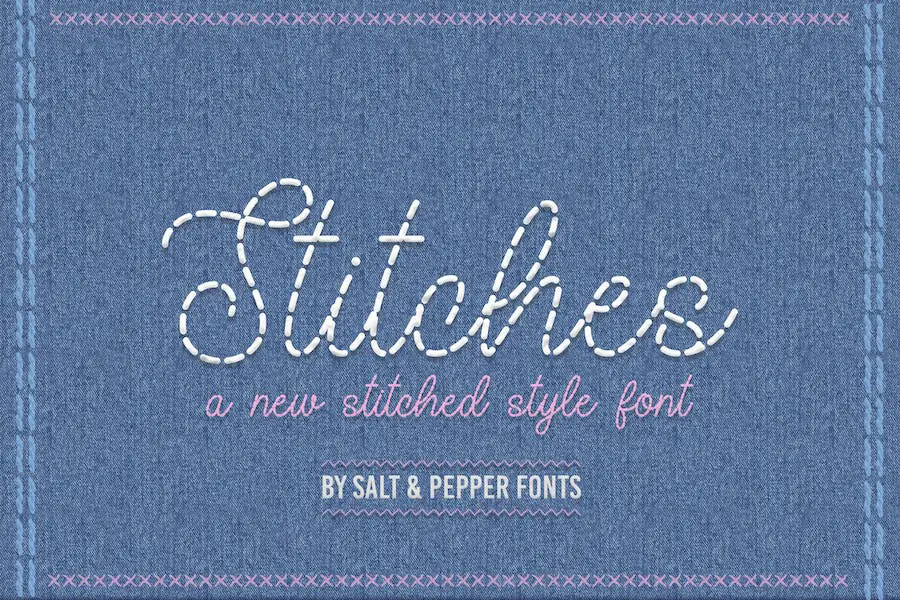
Bienvenido a mi reseña de la fuente Stitches, una fuente de escritorio que aporta el estilo del bordado y la costura a tus proyectos de diseño.
cherolina
Cherolina es una fuente versátil que ofrece un conjunto completo de letras mayúsculas y minúsculas, números, símbolos multilingües, puntuación y ligaduras.
También presenta elementos de diseño únicos, como caracteres decorativos iniciales y finales en minúsculas cortas, así como caracteres decorativos finales en minúsculas, lo que lo convierte en una excelente opción para invitaciones y monogramas.
La textura suave de la fuente la hace adecuada para una variedad de técnicas de impresión, incluido el bordado, el corte por láser y el estampado de oro.
Denalova
Denalova es una fuente de bordado exquisita que ofrece un conjunto completo de letras mayúsculas y minúsculas, junto con símbolos, números, puntuación y ligaduras multilingües.
Lo que distingue a Denalova de otras fuentes es la inclusión de características únicas, como caracteres decorativos iniciales y finales en minúsculas cortas, así como caracteres decorativos iniciales y finales en minúsculas largas.
Con Denalova, los diseñadores gráficos que buscan elevar el diseño de sus proyectos encontrarán una fuente versátil que aporta elegancia y encanto a cualquier diseño. Ya sea que esté trabajando en portadas de libros con un tema medieval o necesite un monograma o una fuente de caligrafía para bordar a máquina o a mano, Denalova seguramente satisfará sus necesidades.
Hermosamente
Beautifully es una fuente script exquisita que combina elegancia, modernidad y un toque de clase. Esta fuente es perfecta para una amplia gama de proyectos de diseño, incluidos logotipos, marcas, invitaciones, papelería, diseños de bodas y publicaciones en redes sociales.
Con sus hermosas curvas y detalles refinados, Beautifully añade un toque de sofisticación a cualquier proyecto. Si eres un diseñador gráfico profesional o alguien que busca mejorar sus proyectos personales, esta fuente seguramente te impresionará.
Es lo suficientemente versátil como para usarse en diferentes plataformas y software, incluidos Google, Adobe, Canva, Circuit, Figma e incluso para diseños de tatuajes. Con Beautifully, puedes lograr sin esfuerzo un resultado pulido y visualmente atractivo. Entonces, ¿por qué esperar? Eleva tus diseños con el fascinante encanto de Beautifully.
Gran belleza gorda
Big Fat Beauty es una fuente Casual Script diseñada para varios proyectos de diseño. Sus atributos lo hacen perfecto para crear un tema informal, logotipos, materiales de marca, carteles, citas, bellos artículos de papelería, publicaciones llamativas en redes sociales y lindas tarjetas de felicitación, entre otros diseños.
Esta fuente es versátil y añade un toque de belleza a cualquier proyecto. Ya sea que sea un diseñador gráfico que trabaja en un logotipo o un blogger que crea publicaciones en las redes sociales, Big Fat Beauty seguramente mejorará su diseño y lo hará destacar del resto.
Entonces, ¿por qué no intentarlo y ver la diferencia que puede marcar en sus proyectos?
Bulvarante
Bulvaryante es una fuente de escritura informal llamada 'Big Fat Beauty'. Es perfecto para una variedad de proyectos de diseño, incluidos temas informales, logotipos, marcas, carteles, citas y hermosos diseños de papelería.
Con su estilo llamativo, también es ideal para crear publicaciones cautivadoras en las redes sociales y lindas tarjetas de felicitación. Esta fuente añade un toque de encanto y singularidad a cualquier diseño.
Café Temprano
Early Coffee es una fuente monolínea manuscrita que sirve para múltiples propósitos. Ya sea que esté buscando agregar un toque de elegancia a su bordado de caligrafía, crear un atractivo letrero de cafetería o menú de cafetería, o simplemente desee una fuente de caligrafía única y moderna, esta fuente lo tiene cubierto.
Su versatilidad se extiende más allá de estas aplicaciones, ya que también se puede utilizar para citas, pancartas, logotipos, empaques de productos, títulos, encabezados, listas de menús y tarjetas de invitación. Esta fuente es perfecta para diversas ocasiones, como baby showers, bodas, cumpleaños, acción de gracias, Navidad y San Valentín.
Con Early Coffee, puedes realzar el diseño de tu proyecto y hacer que se destaque con una fuente manuscrita hermosa y elegante.
rossi
Rossie es una fuente de caligrafía moderna diseñada para agregar un toque elegante, chic y moderno a tus diseños.
Con sus funciones OpenType, que incluyen ligaduras, alternativas, caracteres decorativos finales, números y puntuación, además de compatibilidad con otros idiomas, esta fuente ofrece versatilidad y creatividad.
La textura suave de Rossie lo hace adecuado para diversas técnicas de impresión, como bordado, corte por láser, Cricut y lámina dorada. Ya sea que esté trabajando en un proyecto que requiere sofisticación o buscando una apariencia elegante y contemporánea, Rossie es la elección perfecta.
Historias de llamadas
Callstories es una fuente excepcional que ofrece una variedad de características para mejorar sus proyectos de diseño. Con compatibilidad OpenType, incluye ligaduras, alternativas, caracteres floridos iniciales y finales, números y puntuación.
Esta fuente también es versátil, admite varios idiomas y se adapta bien a diferentes técnicas de impresión como bordado, corte por láser, Cricut y lámina dorada. Su textura suave añade un toque de elegancia, chic y modernidad a tus diseños.
Si buscas una fuente que combine estilo y funcionalidad, Callstories es la elección perfecta para ti.
signatario
Signatie es una fuente de firma elegante que agrega elegancia, elegancia y modernidad a sus diseños. Es perfecto para diseñadores gráficos que desean realzar sus proyectos con un toque de sofisticación.
Esta fuente viene con funciones OpenType, que incluyen ligaduras y caracteres decorativos finales, así como soporte para números, puntuación y múltiples idiomas.
Su textura suave lo hace adecuado para diversas técnicas de impresión como bordado, corte por láser, Cricut y lámina dorada. Con Signatie, puedes crear sin esfuerzo diseños impresionantes y de apariencia profesional.
Arrancador de banda de rodadura
Tread Starter es una fuente de escritura monolínea informal que es perfecta para varios proyectos de diseño.
Sus atributos incluyen ser adecuado para temas informales, logotipos, marcas, carteles, citas, exhibidores, bellos artículos de arte, publicaciones llamativas en redes sociales y lindas tarjetas de felicitación, así como cualquier otro diseño que puedas imaginar.
bosque
Forestea es una fuente de caligrafía moderna que aporta elegancia, elegancia y modernidad a tus diseños.
Con sus características OpenType, que incluyen ligaduras, alternativas, caracteres floridos iniciales y finales, números y puntuación, esta fuente no solo es versátil sino que también admite múltiples idiomas.
Su textura suave lo hace adecuado para diversas técnicas de impresión como bordado, corte por láser, Cricut y lámina dorada. Ya sea que esté trabajando en invitaciones, tarjetas de felicitación, logotipos o cualquier otro proyecto de diseño, Forestea es la elección perfecta.
Las mejores fuentes de bordado gratuitas
¿Busca mejorar sus proyectos de bordado con fuentes únicas y llamativas? ¡No busque más! En este artículo, hemos compilado una lista de las mejores fuentes de bordado gratuitas que seguramente llevarán tus diseños al siguiente nivel.
Así que no te lo pierdas: ¡sigue leyendo y descubre la fuente perfecta para tu próxima obra maestra de costura!
Bordado VTKS
VTKS Bordado es una fuente perfecta para diseñadores gráficos que buscan elevar el diseño de sus proyectos. Es una fuente gratuita creada por Douglas Vitkauskas y está disponible para uso personal.
La fuente VTKS Bordado agrega un toque único a cualquier diseño con sus patrones intrincados y detallados. Presenta un aspecto artesanal, lo que le da a sus proyectos una sensación artística y personalizada.
Esta fuente es una excelente opción para agregar un toque de elegancia y sofisticación a tus diseños.
Puntada Hovden
Hovden Stitch es una fuente de bordado exquisita que es perfecta para diseñadores gráficos que buscan mejorar el diseño de sus proyectos. Creada por Douglas Vitkauskas, esta fuente está disponible para uso personal gratuito.
Con Hovden Stitch podrás añadir un toque de elegancia y sofisticación a tus diseños. Sus intrincados detalles de costura le dan a su texto un aspecto único y artesanal que seguramente captará la atención.
Cada letra de la fuente ha sido diseñada meticulosamente para parecerse al arte del bordado, creando un impacto visual impresionante. Ya sea que estés trabajando en un póster, un logotipo o cualquier otro proyecto de diseño, Hovden Stitch elevará la estética general y hará que tu trabajo se destaque.
Bordado De Reyes
Kingthings Bordado es una fuente versátil que es perfecta para diseñadores gráficos que buscan mejorar los diseños de sus proyectos. Con su efecto de costura único, esta fuente añade un toque de creatividad y encanto a cualquier diseño.
Creada por Rasmus Andersson, la fuente Hovden Stitch ofrece una amplia gama de atributos que la distinguen de otras fuentes de bordado.
Su intrincado detalle de costura le da un aspecto realista y artesanal, lo que lo hace ideal para diseños con una estética hecha a mano o vintage.
Adiós Crewel
Goodbye Crewel es un alfabeto de muestra de country clásico conocido como It World NF Font, creado por Nick's Fonts. Esta fuente es perfecta para diseñadores gráficos que buscan realzar sus proyectos con un toque de elegancia y singularidad.
Con su atractivo atemporal, Goodbye Crewel añade un toque encantador y rústico a cualquier diseño.
Elaborado por Nick's Fonts, Goodbye Crewel está meticulosamente diseñado para capturar la esencia del bordado tradicional. Sus intrincados detalles y sus curvas cuidadosamente elaboradas le dan una calidad artesanal que puede realzar cualquier proyecto.
Jersey navideño
Christmas Jumper de SpideRaYsfoNtS es una fuente diseñada para proyectos personales, específicamente Xmas Knit Font. La fuente ahora está disponible como material de donación a través de Charity Fonts, y las ganancias se destinarán a apoyar Save the Children It Day 2014.
Esta encantadora fuente es perfecta para añadir un toque festivo a tus proyectos. Con su diseño único, captura el espíritu acogedor y alegre de la Navidad.
Ya sea que esté creando gráficos con temas navideños, invitaciones o incluso etiquetas de regalo personalizadas, Christmas Jumper agrega un elemento divertido y caprichoso.
Callejear
Gaby de Eva Barabasne Olasz es una fuente que sirve como demostración para probar en tu computadora. Con caracteres limitados, permite a los diseñadores gráficos evaluar su compatibilidad con sus proyectos.
Esta fuente ofrece un diseño único y elegante, perfecto para añadir un toque de creatividad a cualquier proyecto. Sus caracteres limitados pueden verse como un inconveniente, pero también brindan la oportunidad de probar la versatilidad de la fuente y ver cómo complementa diferentes elementos de diseño.
La simplicidad de Gaby hace que sea fácil de leer y comprender, asegurando que su mensaje llegue claramente a su audiencia. Sus líneas limpias y sus distintas formas de letras añaden un toque moderno y elegante a cualquier diseño.
Preguntas frecuentes
Las fuentes de bordado son una colección de letras, números y símbolos prediseñados que se pueden coser en tela con una máquina de bordar. Estas fuentes te permiten agregar texto personalizado a tus proyectos de bordado, ya sea un monograma, un nombre o una frase.
Al elegir una fuente de bordado, considere el estilo y el propósito de su proyecto. Las fuentes vienen en varios estilos, como script, block, serif y sans-serif. Si vas a bordar un artículo formal como un pañuelo de boda, una fuente de escritura sofisticada puede ser una buena opción.
Para un proyecto más informal como un bolso de mano, una fuente en bloque divertida podría funcionar bien. Además, considere el tamaño y la legibilidad de la fuente, ya que los detalles pequeños o intrincados pueden no quedar claros en ciertas telas.
Hay varias fuentes donde puedes encontrar fuentes de bordado. Muchos mercados en línea ofrecen diseños de fuentes de bordado tanto gratuitos como de pago.
Además, los sitios web especializados y foros dedicados al bordado suelen tener una amplia selección de fuentes disponibles para descargar. También puede encontrar fuentes de bordado en programas de software de bordado o incluso crear las suyas propias utilizando un software de digitalización.
Conclusión
En conclusión, cubrimos una variedad de las mejores fuentes de bordado en este artículo, brindándole opciones para mejorar los diseños de sus proyectos. Desde elegantes fuentes serif hasta divertidas fuentes script, hay algo para cada estilo y preferencia.
Recuerde considerar el tono y el tema de su proyecto al seleccionar una fuente, ya que puede tener un impacto significativo en la estética general.